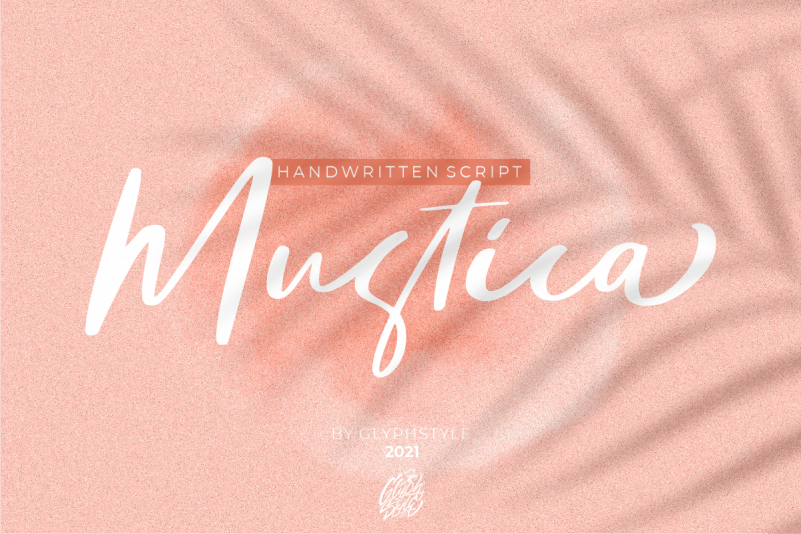
Mustica Handwritten Script Font – Download Grátis
A Mustica Handwritten Script Font é uma elegante escolha para designers buscando um estilo autêntico e sofisticado. Seus traços grossos e finos conferem a impressão de seriedade e delicadeza ao mesmo tempo, resultando num resultado visual que transmite confiabilidade e criatividade simultaneamente. Esta fonte é perfeitamente adaptada para criar marcas de água, logotipos, cartões de visita, embalagens de produto e outras identificações visuais. O seu aspecto natural, com as delicadas traçaduras que resultam da arte manual, criam um toque pessoal em qualquer design. Com uma personalidade única e um acabamento cuidadosamente refinado, a Mustica Handwritten Script Font é um recurso indispensável para quem busca se destacar no mercado de design. Ela traz ao seu trabalho o brilho único que torna cada projeto incomparavelmente interessante.